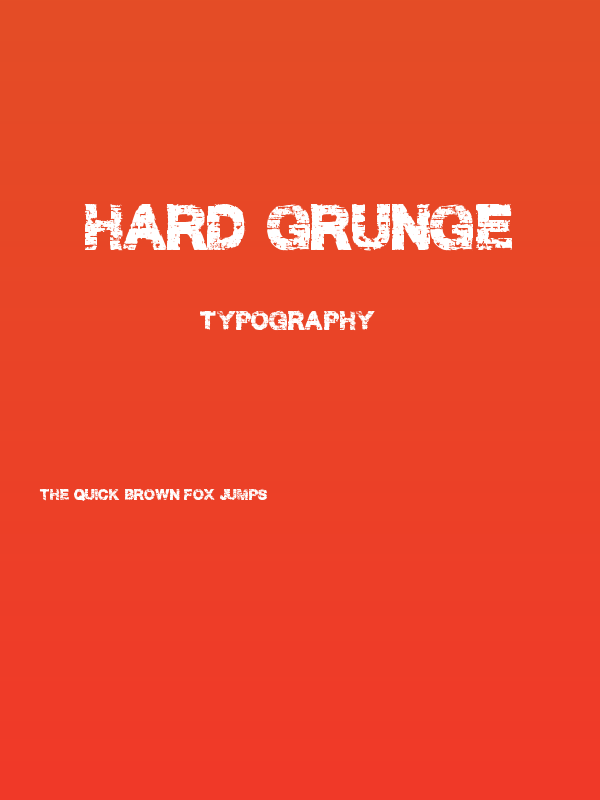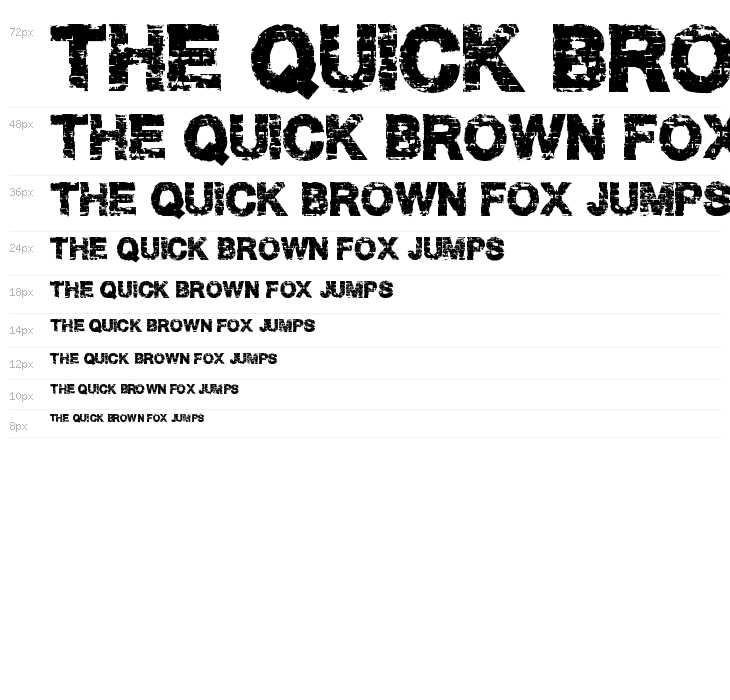
Hard Grunge Font
| Stile generale | Grunge, Edgy |
| Progetti proposti | Ideal for music album covers, posters, urban-themed designs, and rebellious branding. |